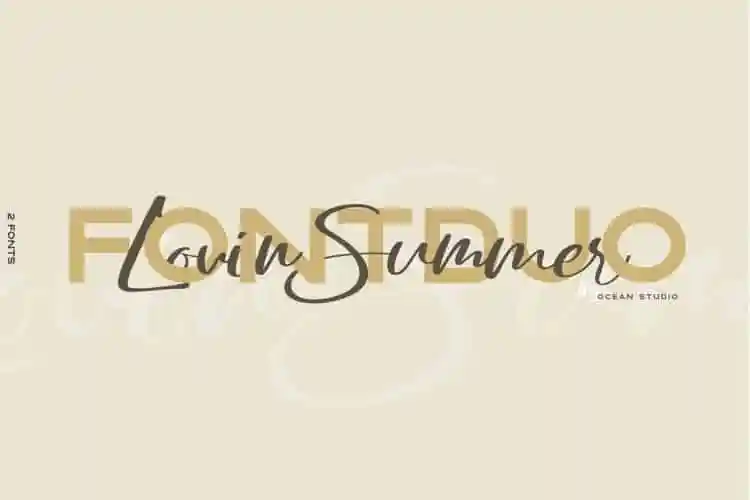
Lovin Summer Script Font – Download Grátis
A fonte Lovin Summer Script é uma combinação única de letra cursiva moderna com tipo geométrico e elegante. Ela dá ao seu texto um aspecto sofisticado, luxuoso e moderno, fazendo dele ainda mais encantador e refinado. Esta font foi criada pelo Ocean Studio e está disponível para download em 99designs. A Lovin Summer Script é perfeitamente adequada para qualquer tipo de design, seja criação de logomarca, marca, citações ou qualquer outro recurso gráfico que você precise. Com uma aparência moderna e sofisticada, essa font não apenas enriquece seu trabalho visuais, mas também o torna único e impecavelmente elegante. Não perca a oportunidade de revolucionar suas criações com a Lovin Summer Script.